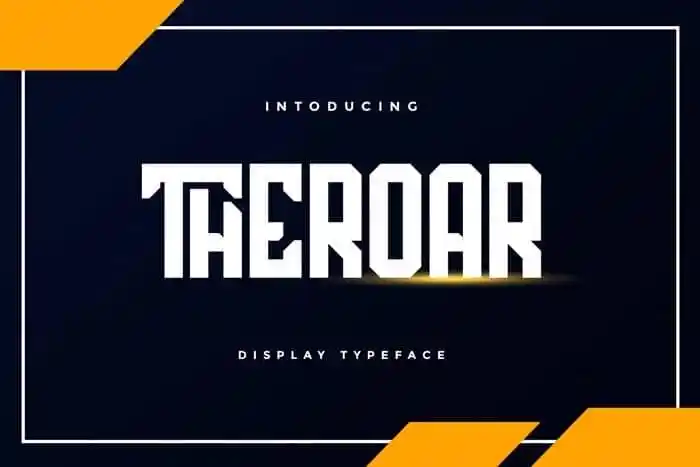
A Theroar Display Font é uma nova escolha para designers que buscam estila e versatilidade em suas criações digitais. Lançada pela 99designs, esta font se destaca por sua simplicidade atraente e diversidade de estilos, criados pelo font designer Rantautype. Ideal tanto para menus ou merchandising quanto para headlines e citações completas, ela oferece um toque vintage mas mantém um encanto futurista. Com alternativas variadas e caracteres especiais que dão uma cara única à sua marca, a Theroar Display Font se destaca como uma fonte indispensável para projetos criativos. Seja ele um projeto editorial ou de design gráfico, essa é uma escolha segura para quem procura arredondar os ângulos e dar vida à mensagem em seu trabalho.